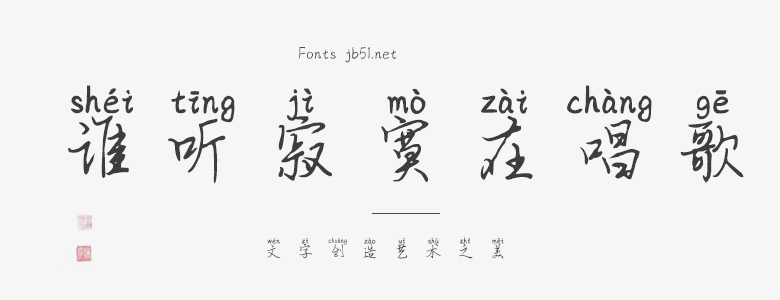
谁听寂寞在唱歌是一款具有独特艺术风格的字体设计。这款字体以其优雅、神秘且富有感情的特点,抓住了使用者的注意力。 "谁听寂寞在唱歌"这个标题,已经暗示了这款字体的情感深度和艺术风格。每一个字母都精心设计,仿佛每个字都是一首短歌,富含着深情和故事。字体的线条流畅,有着优雅的曲线,给人一种温柔和舒适的感觉。 这款字体的最大特点是其艺术性和感情投入。通过字体的形状和线条,可以感受到设计师的情感和思想。例如,字母“w”的形状,就像一对相互拥抱的恋人,表达出温暖和深情。而字母“i”的一点,就像一颗心,表达出爱和感情。 谁听寂寞在唱歌这款字体非常适合用于一些需要表达深度和情感的主题,比如心情日记、爱情小说、情感散文等。通过使用这款字体,不仅可以增强文本的情感深度,而且还可以给读者带来一种独特的阅读体验。 总的来说,谁听寂寞在唱歌是一款富有感情和艺术性的字体设计。无论是在标题设计、文章内容还是其他文字表达的场合,它都能帮助传递出深度的情感和故事。